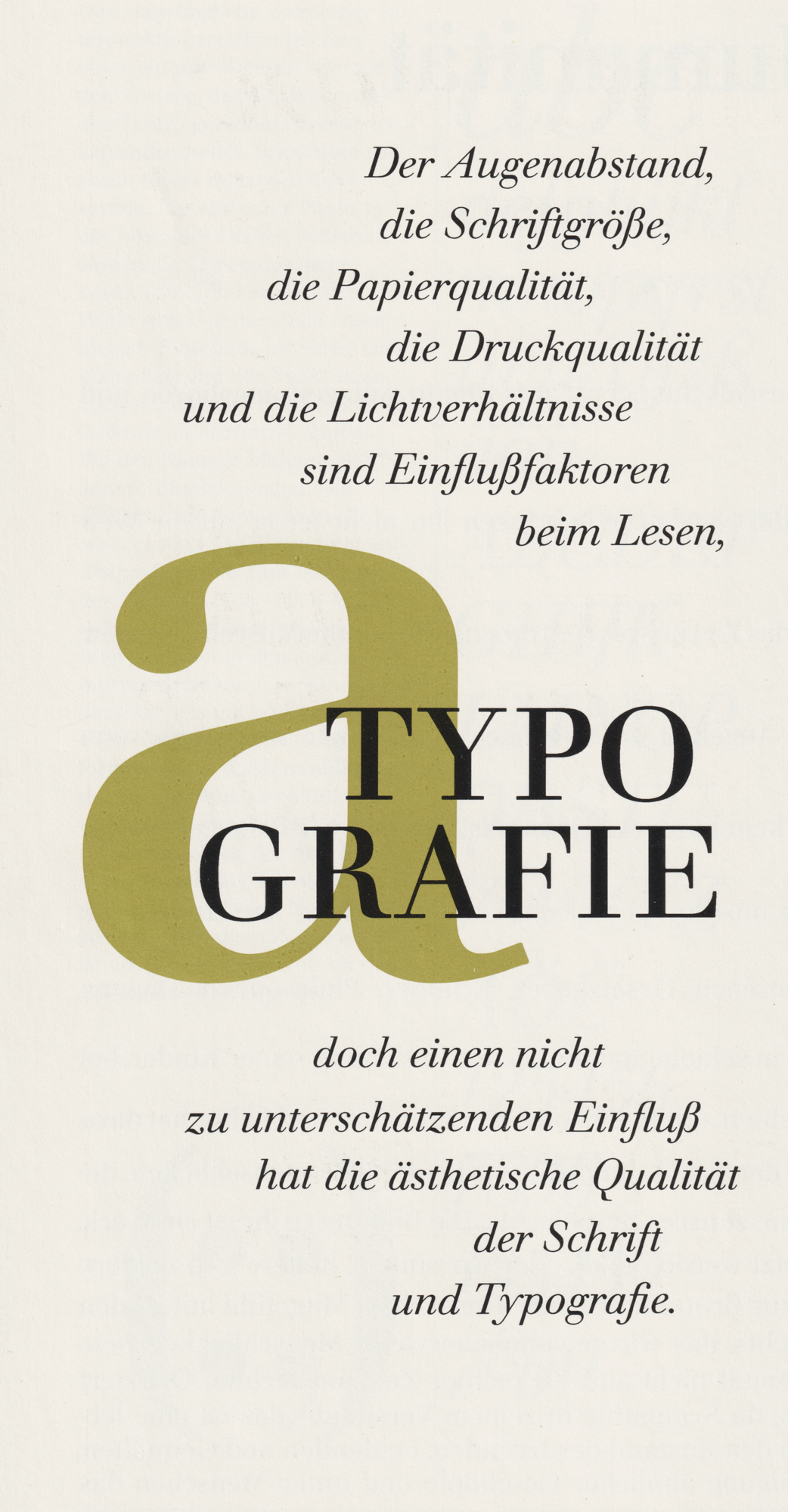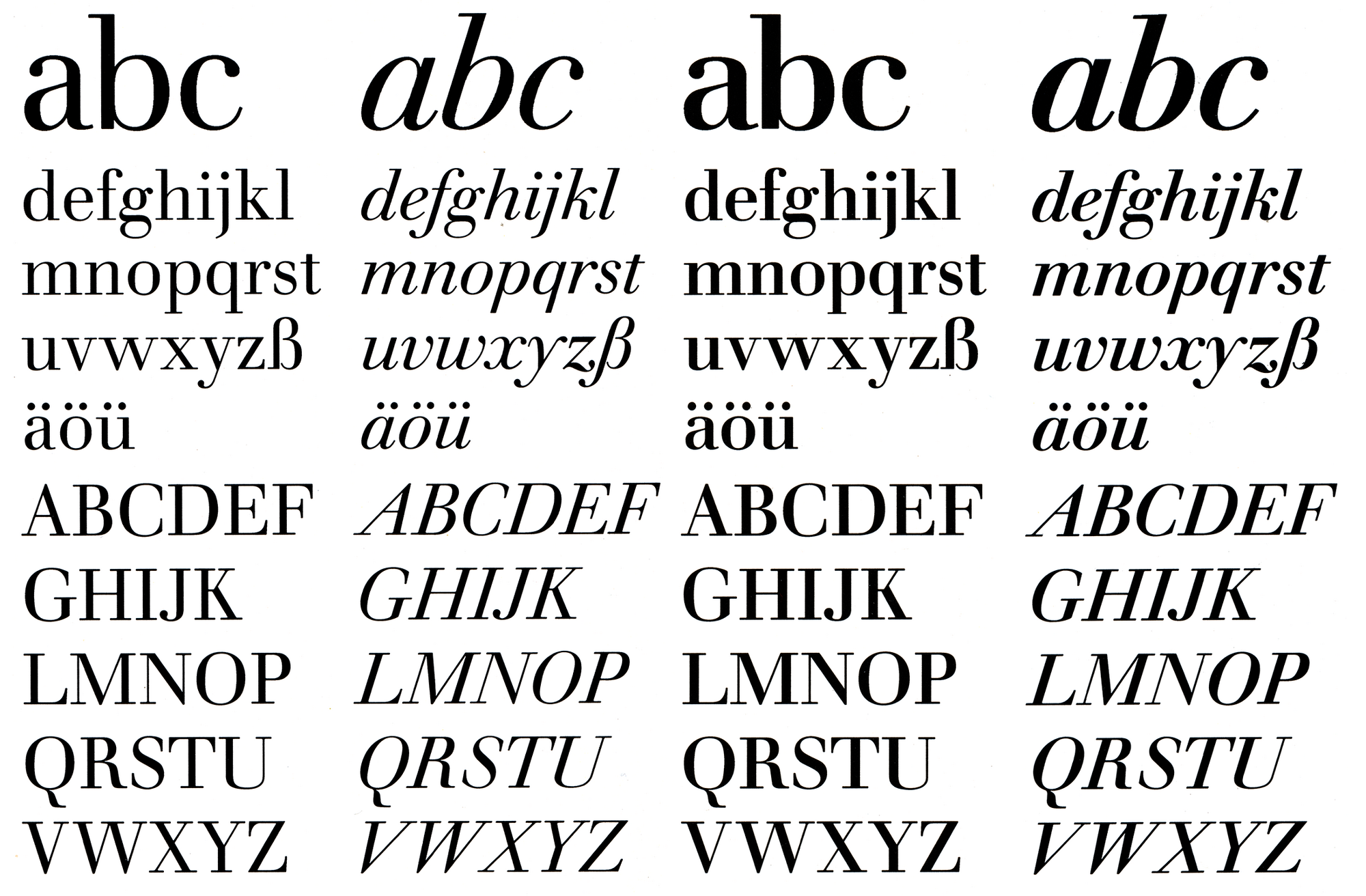
Die Walbaum ist benannt nach ihrem Schöpfer Justus Erich Walbaum, der sie um 1800 als klassizistische Schrift schuf. Weithin bekannt wurde die Schrift jedoch erst im 20. Jahrhundert durch die Neuauflage durch Brockhaus und die H. Berthold AG. Bei Typoart wurde die Schrift in den 1980er-Jahren durch Hans-Peter Greinke für den Fotosatz neu bearbeitet und erschien in den Garnituren mager, kursiv, halbfett und halbfett kursiv.
Eine digitale Version auf Basis der Fotosatzversion erschien durch Elsner+Flake in drei optischen Größen: TB (4 Schnitte), TH (4 Schnitte), TI (2 Schnitte).